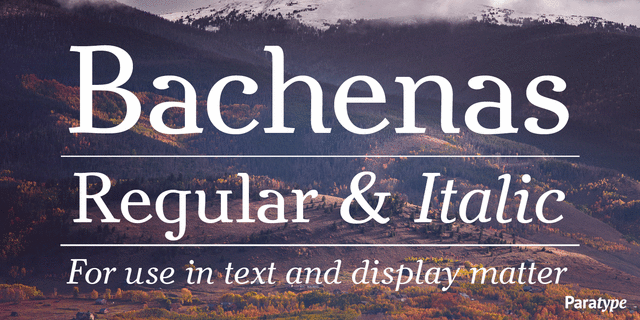
Гарнитура разработана для Отдела новых шрифтов НИИ Полиграфмаш в 1963 году литовским художником книги Витольдасом Баченасом. Шрифт относится к типу малоконтрастной антиквы с некоторыми необычными деталями. Предназначен для набора текста и акциденции. Цифровая версия разработана для фирмы ParaType в 2003 году (дизайнер Любовь Кузнецова).
Ассоциации c семейством BachenasКачества и характер:
Игривый, музыкальный, звонкий, элегантный, изысканный, оригинальный, свежий, вкусный, художественный, нарядный, гостеприимный, интеллигентный, красивый, запоминающийся, приятный, утонченный, аккуратный, европейский, серебристый, гуманитарный, творческий, женственный, ветренный, манерный, няшный, вежливый